吉武工務店 様 「クリエイティブオフィス」
より快適に、創造性豊かに
従来のオフィスの考え方を覆す空間。
それがクリエイティブオフィスです。
各所に置かれた筆文字、筆イラストは、このオフィスで活動する人やオフィスに訪れた人の心をほっとさせるような、そんな効果を生み出しています。
大阪ケイオスカフェ
人が集い、語らい、創造する空間づくり
マツダ株式会社 様「愚足庵」
金属音と機械音が響く工場に、温かな空間が誕生。
株式会社鈴木製作所 様「我逢人」
人との出逢いを、より豊かにする空間作り。
東海化成品株式会社 様
お客様をお出迎えし、精一杯おもてなししたい。
そんな温かな気持ちの伝わる空間。
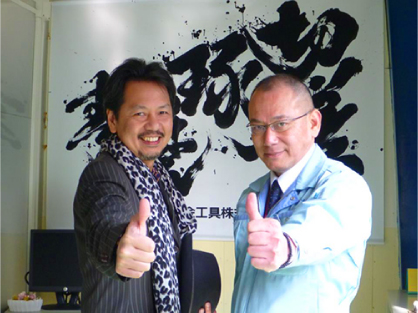
枚岡合金工具株式会社 様
見るたびに鼓舞されるような、力強い決意表明。